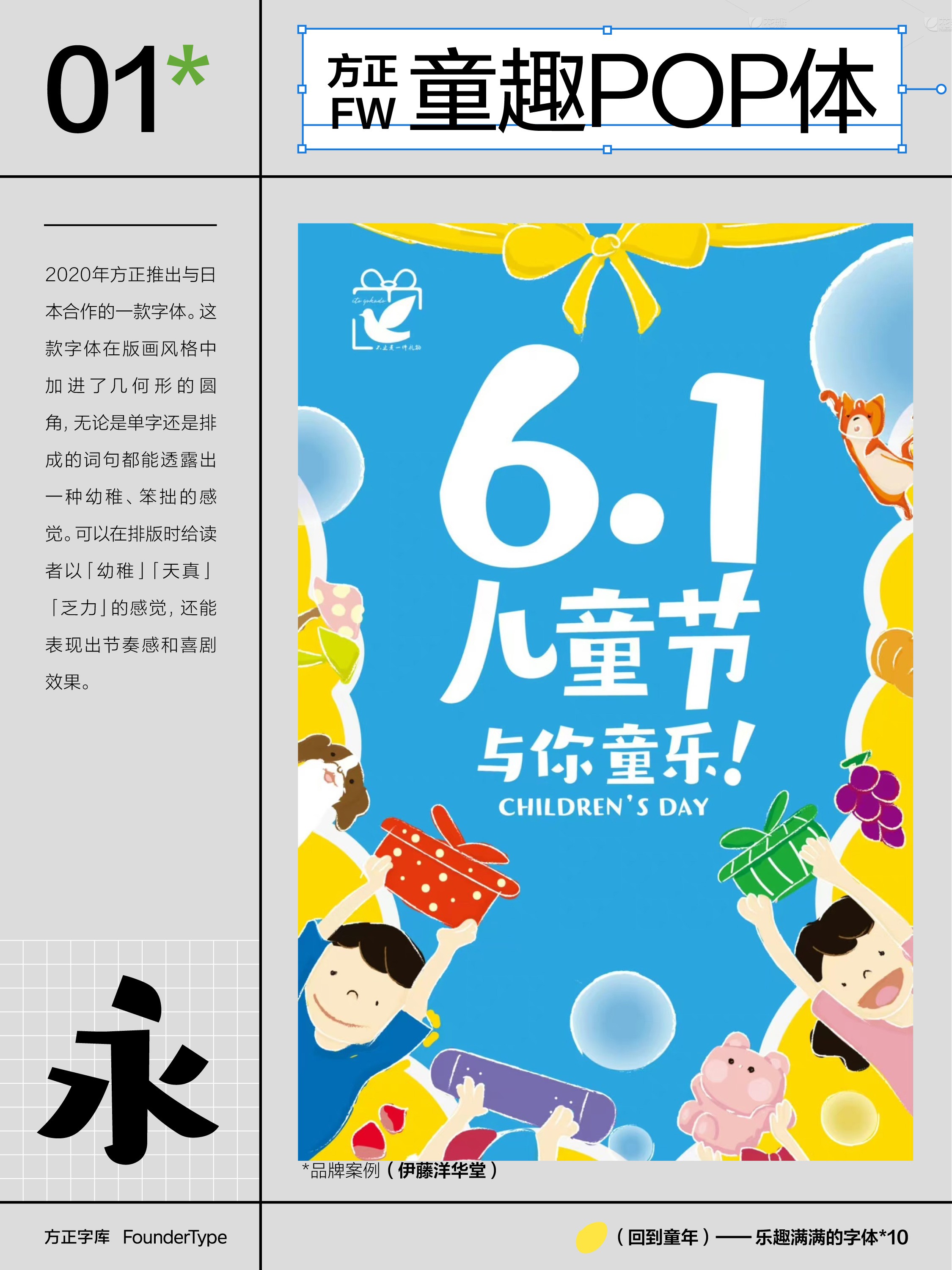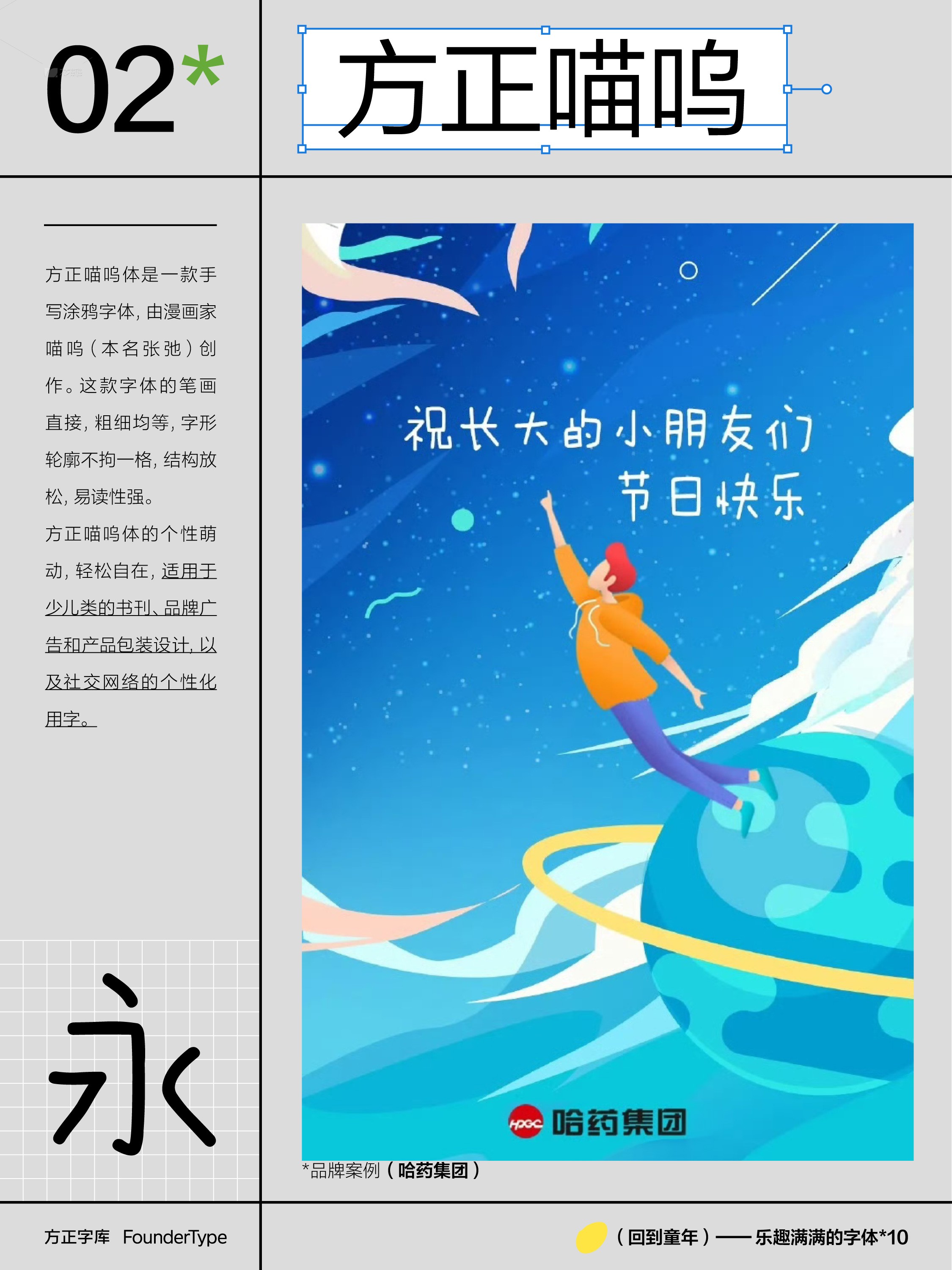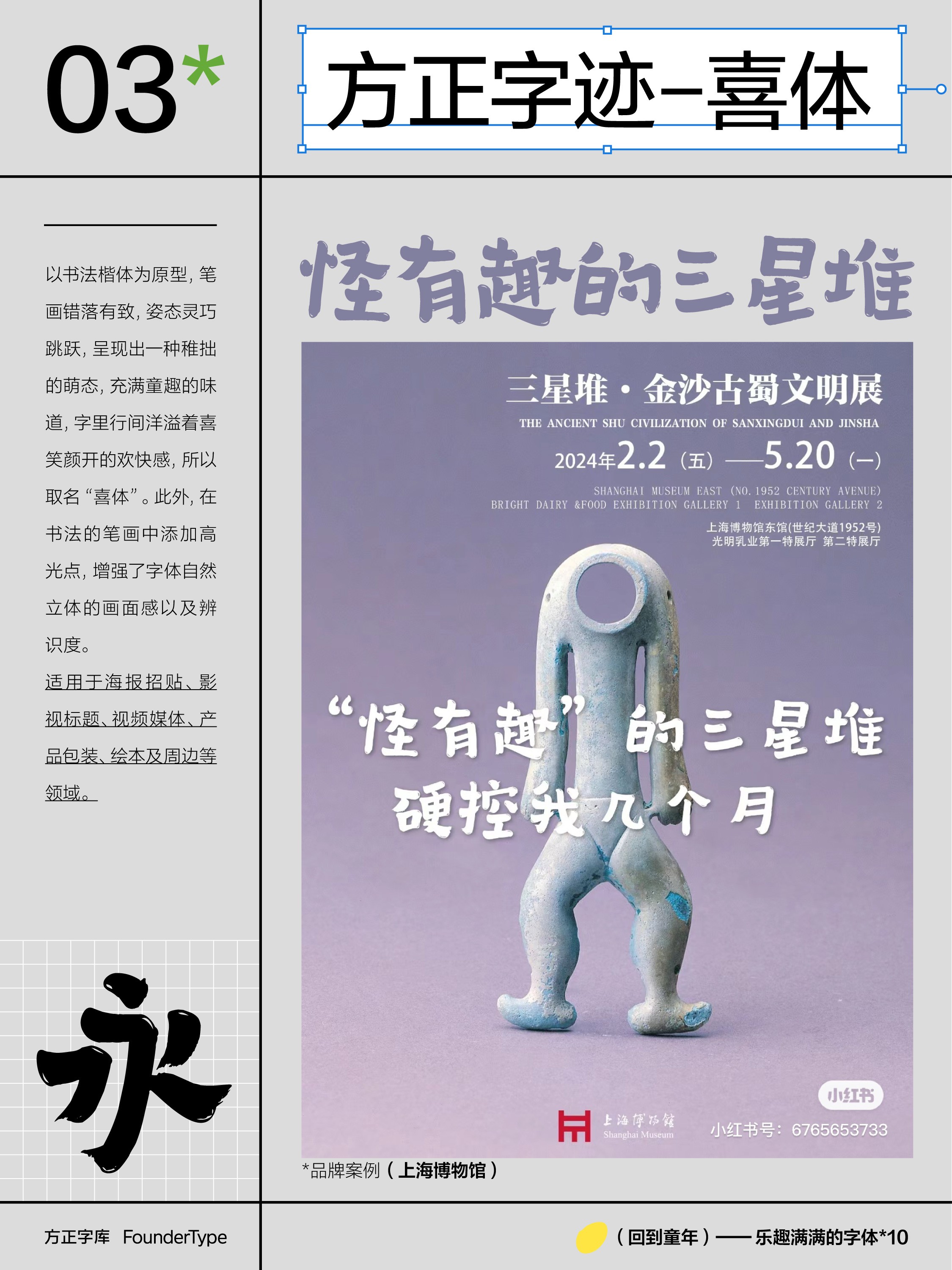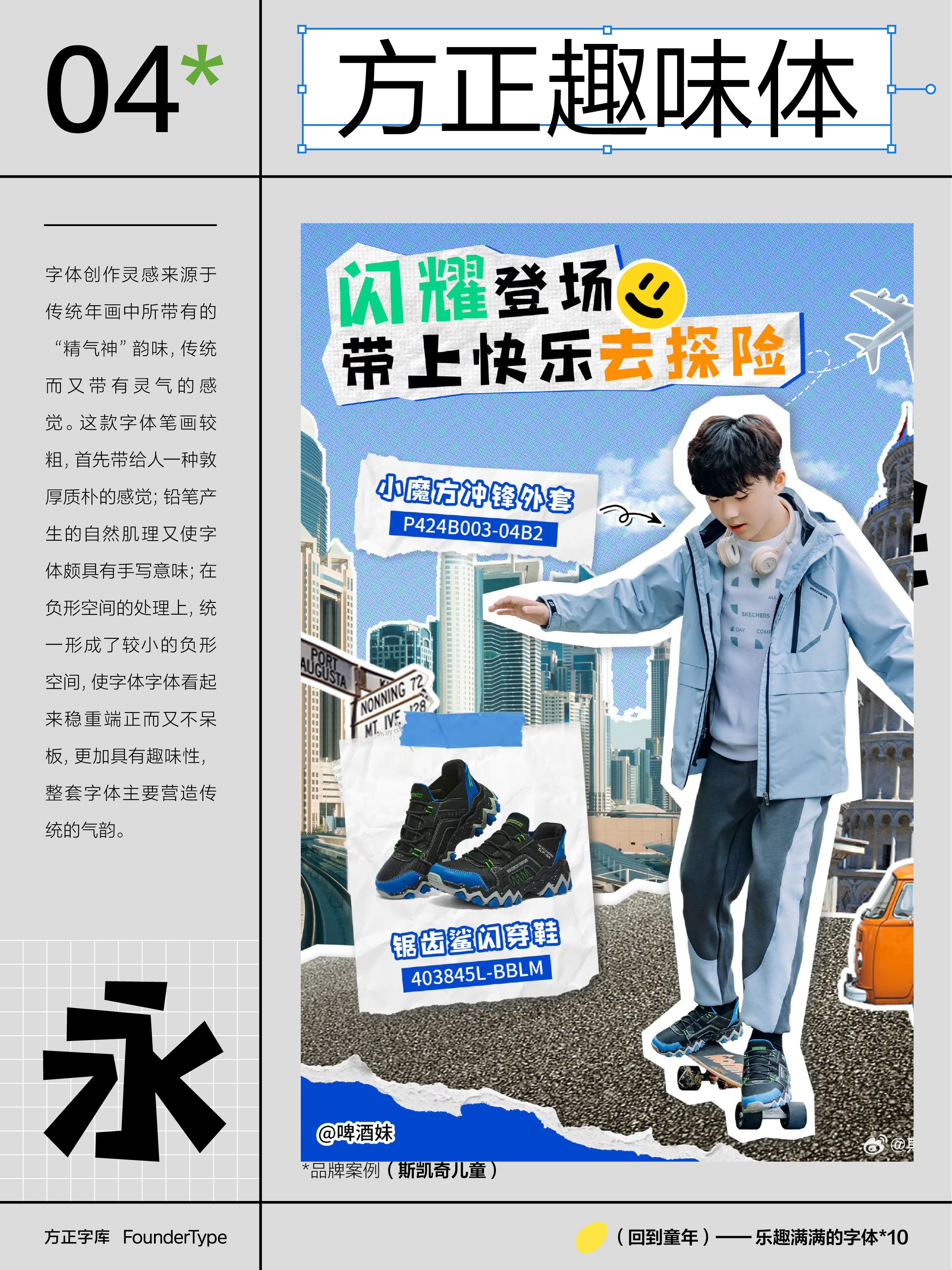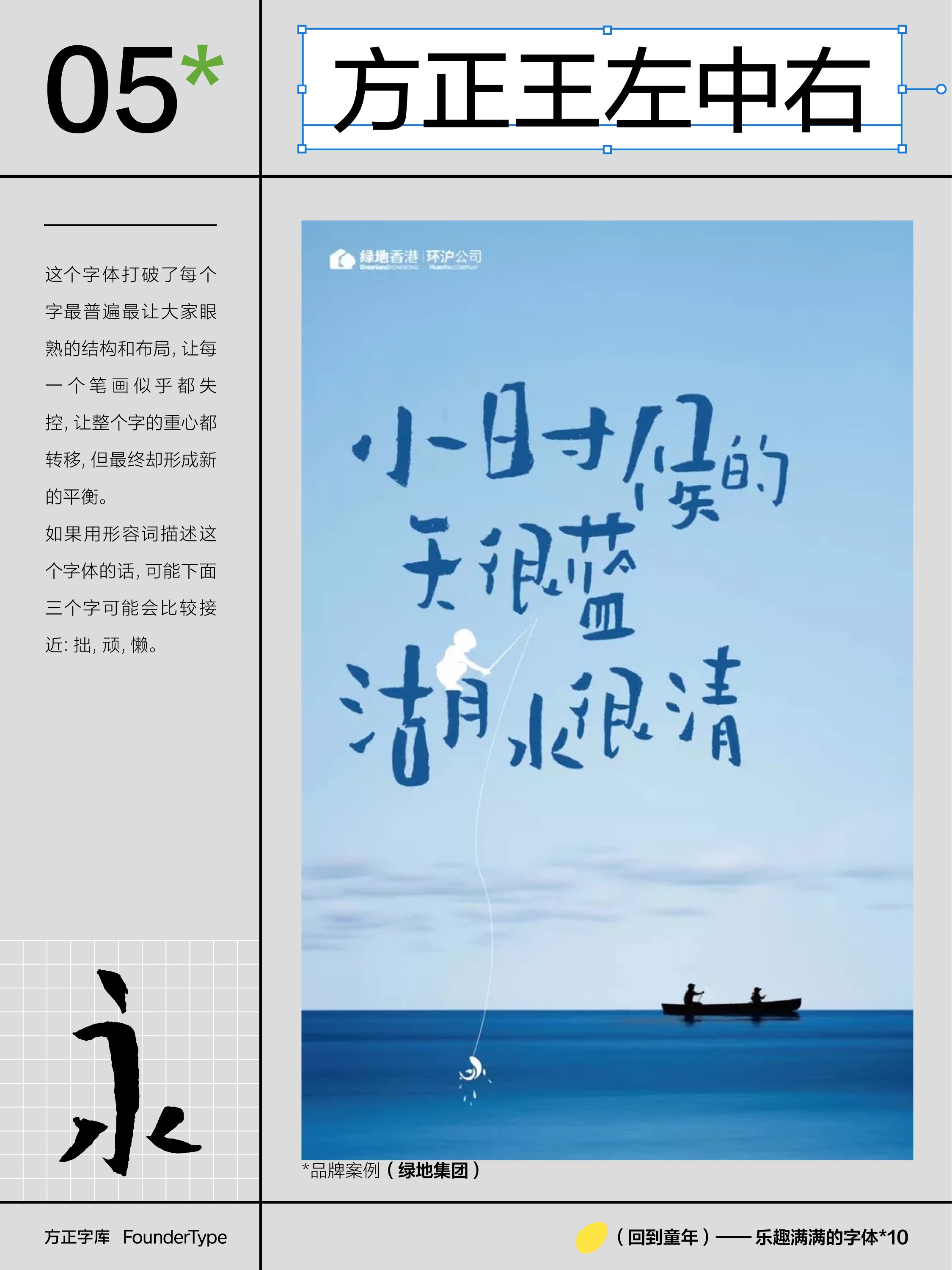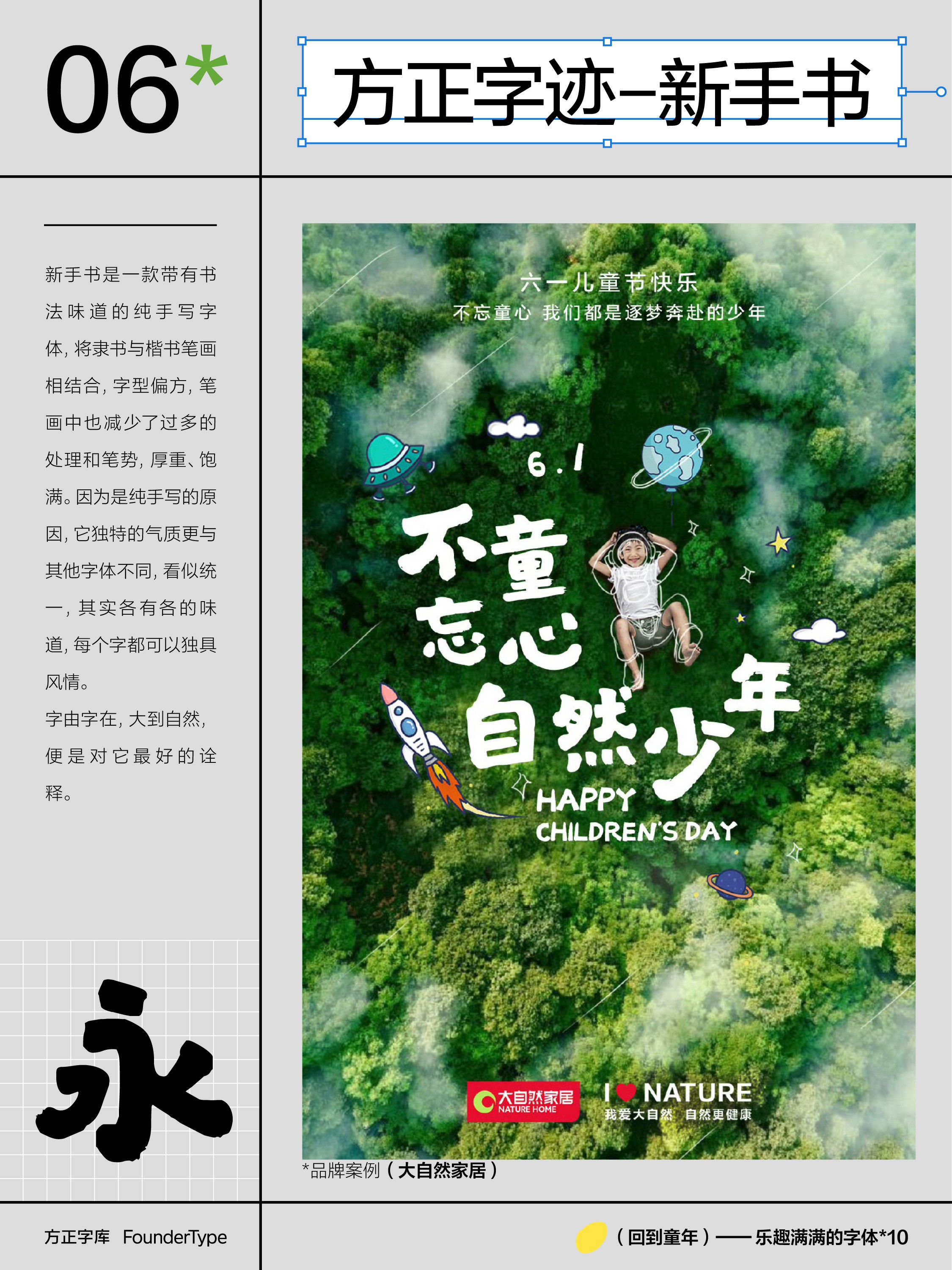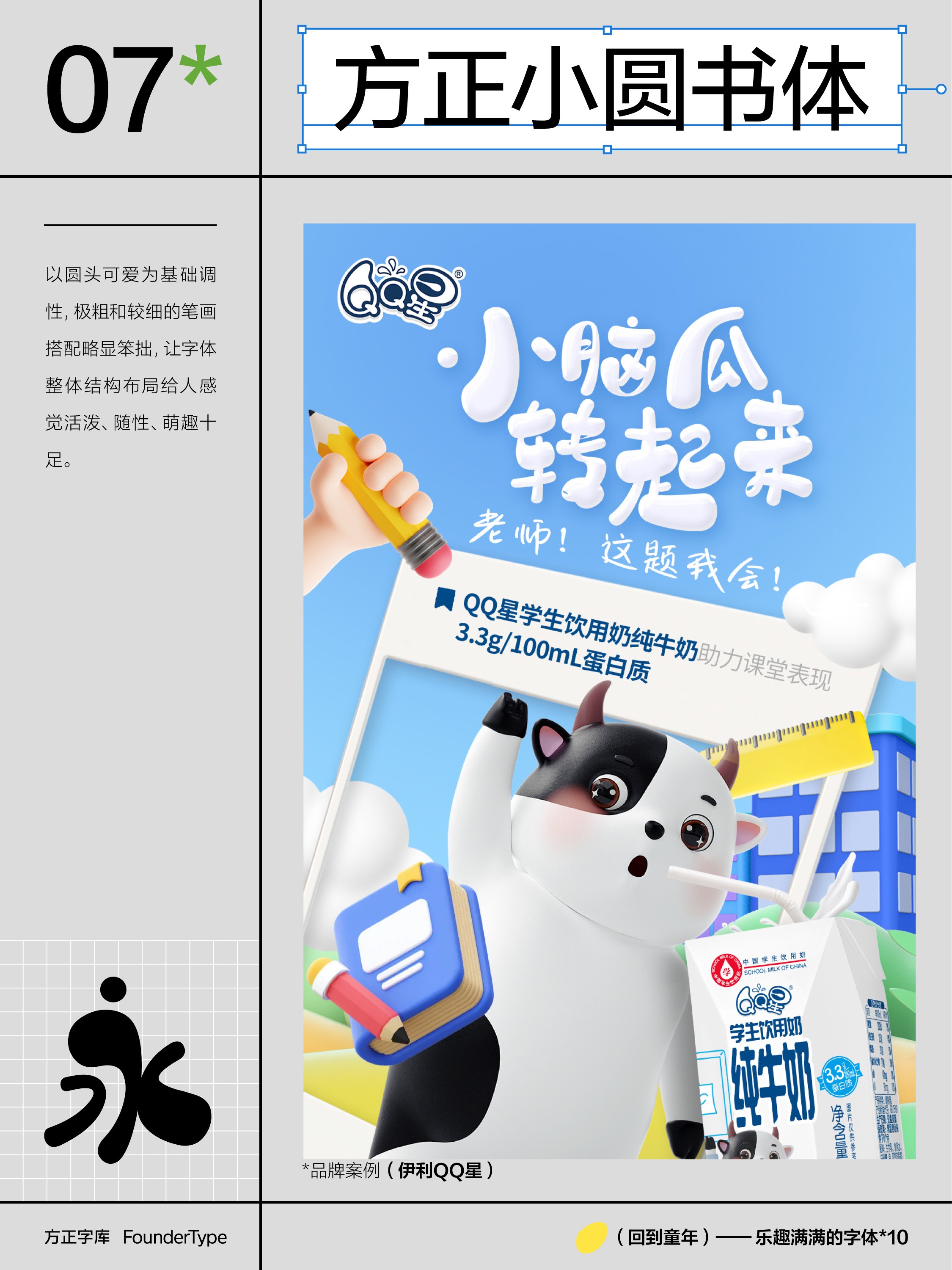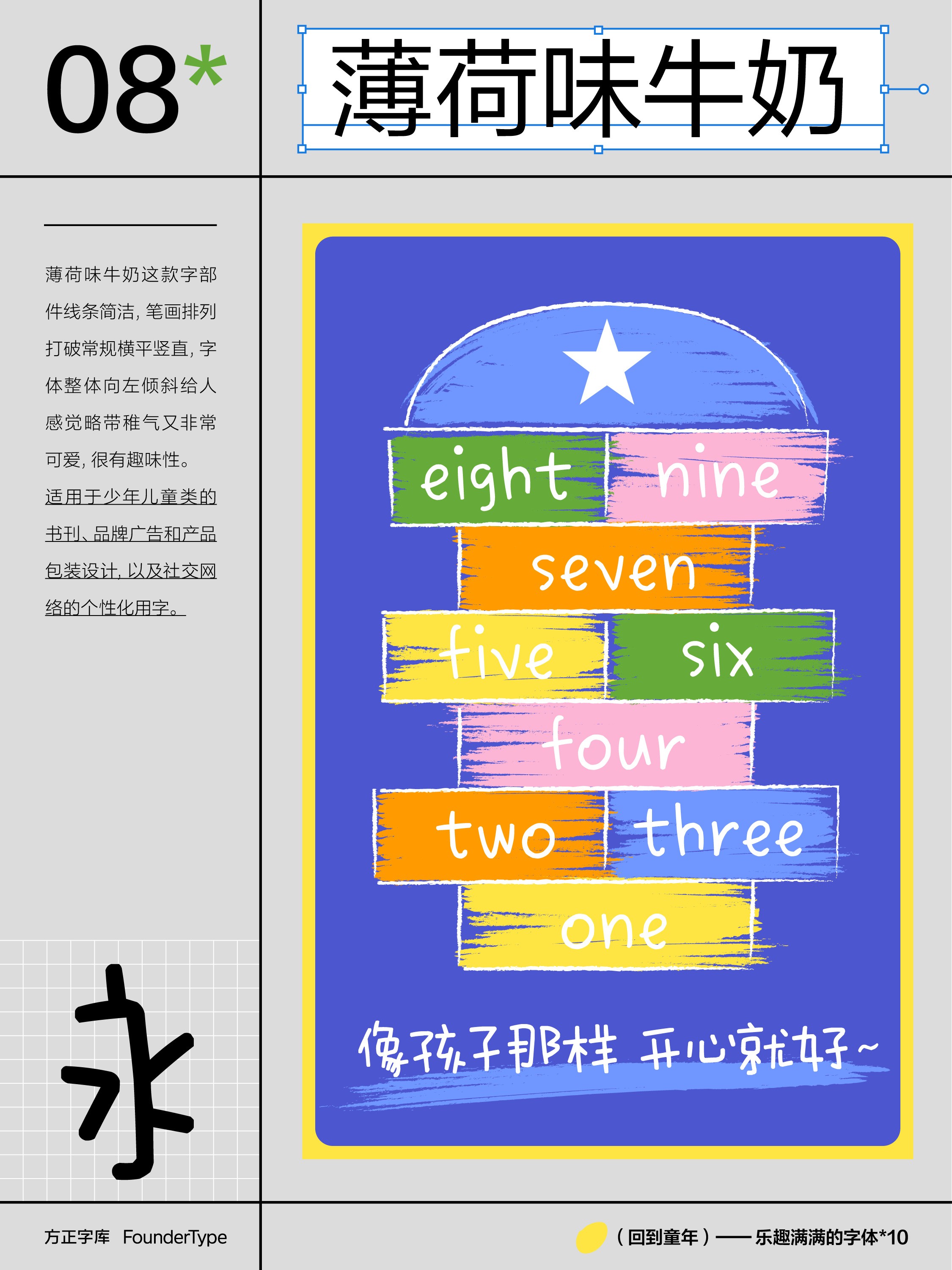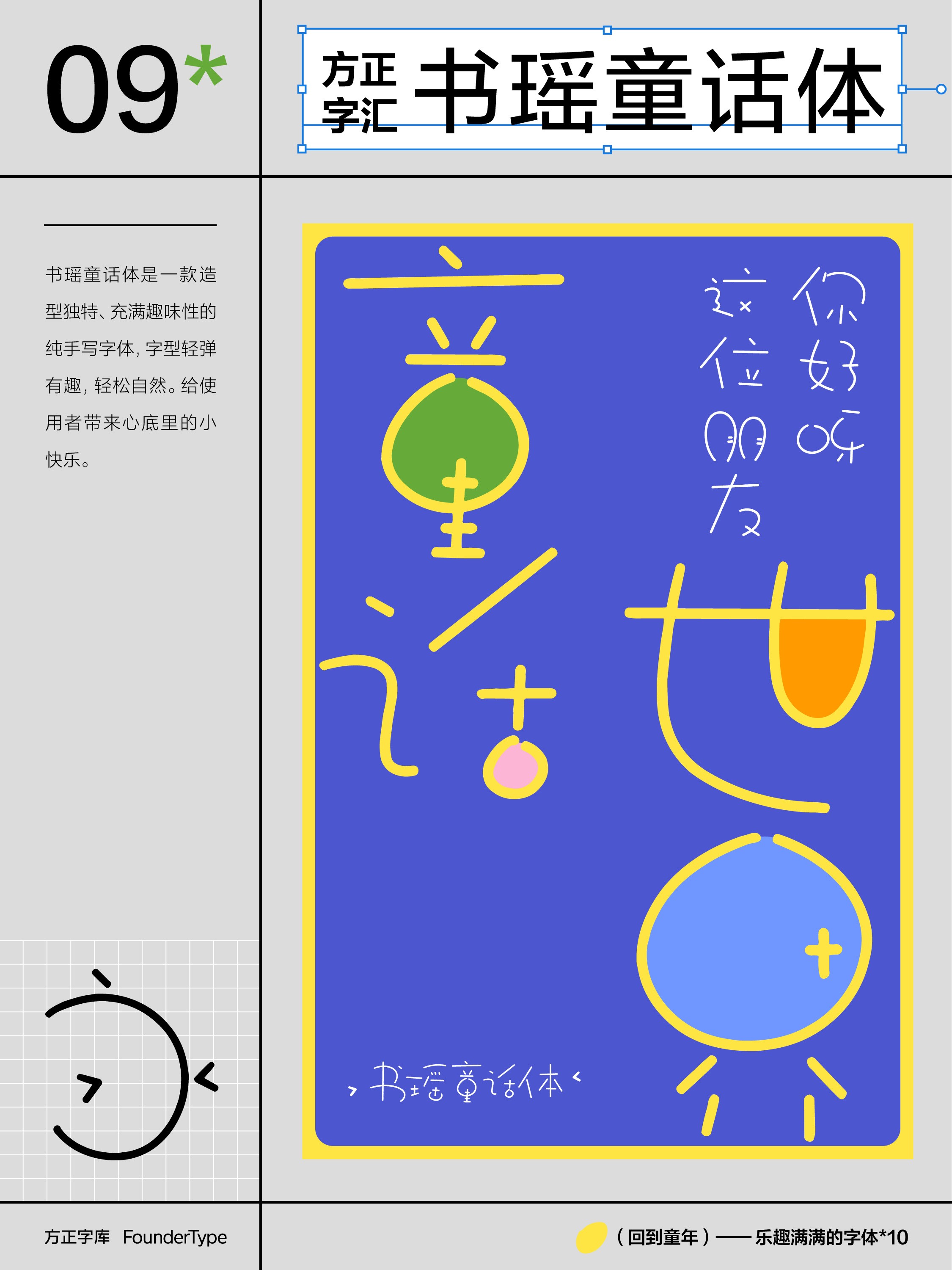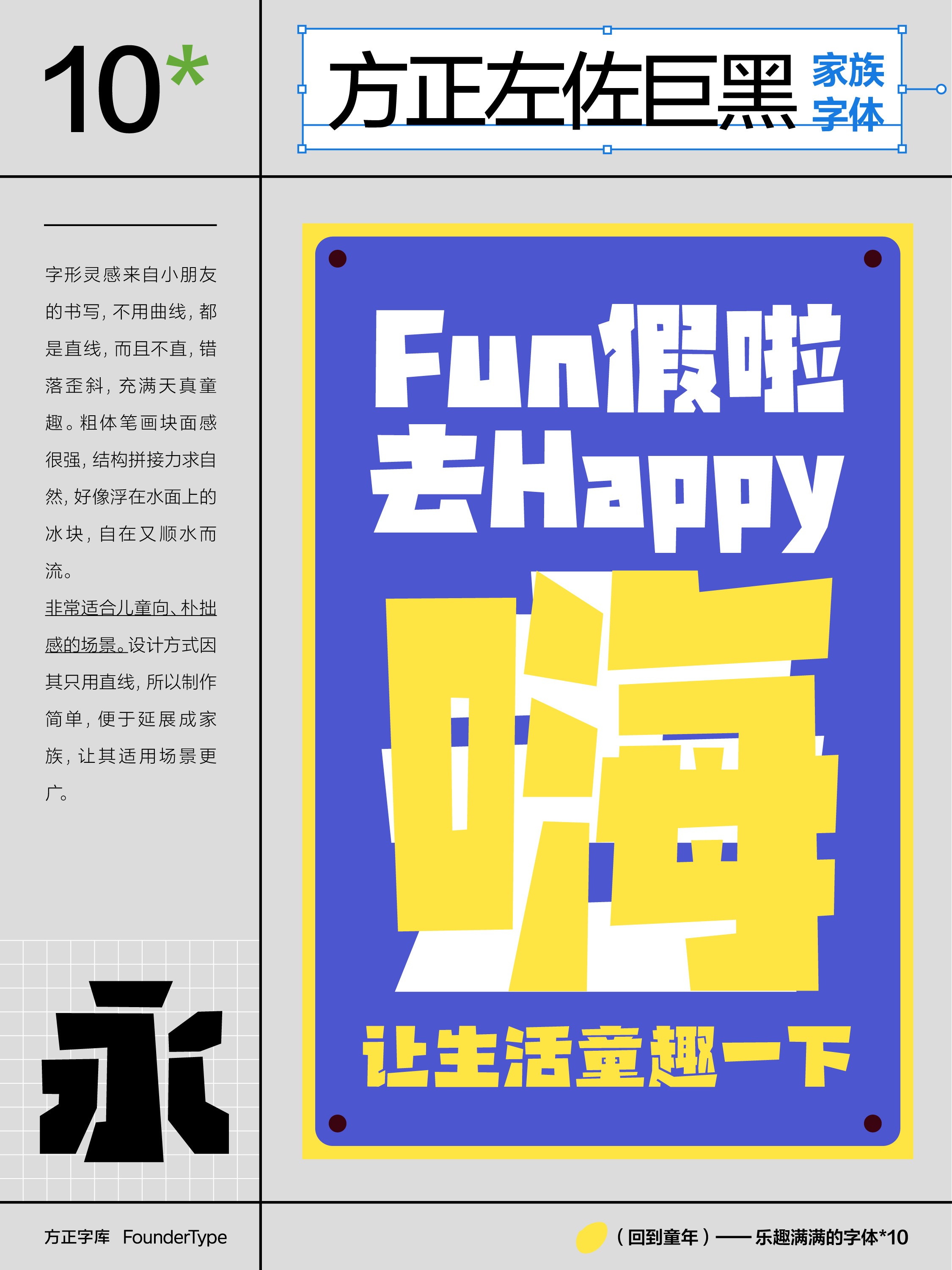
儿童节字体特辑:解锁品牌设计的童趣次元
叮咚!即将抵达六一快乐星球,品牌们准备好接住这波童心暴击了吗?本期10款自带童趣基因的字体组团出道:歪扭的课桌涂鸦尽显稚拙个性,跳房子的粉笔痕变身奇趣笔画,积木哐当一声拼出蠢萌结构,让所有童年符号都化作可传播的视觉语言! 无论是零食包装的趣味标语、亲子产品的治愈文案,还是户外活动的创新设计,这些字体都能为文字注入弹珠汽水般的清爽活力,通过不规则造型与手写质感,触发集体记忆开关,让品牌叙事在童趣滤镜中实现情感共鸣~